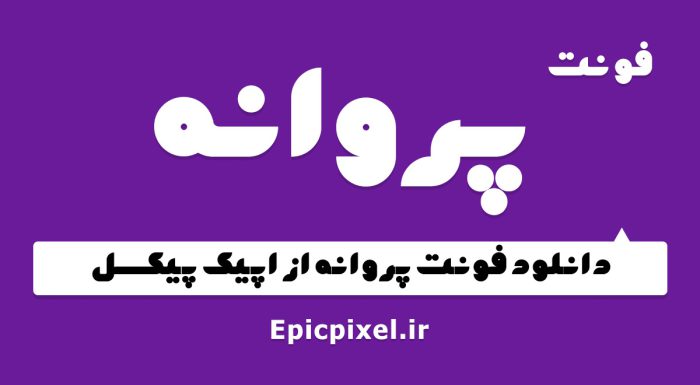
فونت پروانه فارسی
| فونت | فونت دیما پروانه نرمال Font Dima Parvaneh Normal |
فونت پروانه جزو معد ود فونت های خوشگلی هست که نتونستم جلو خودموو بگیرم و همه جا ازش استفاده نکنم